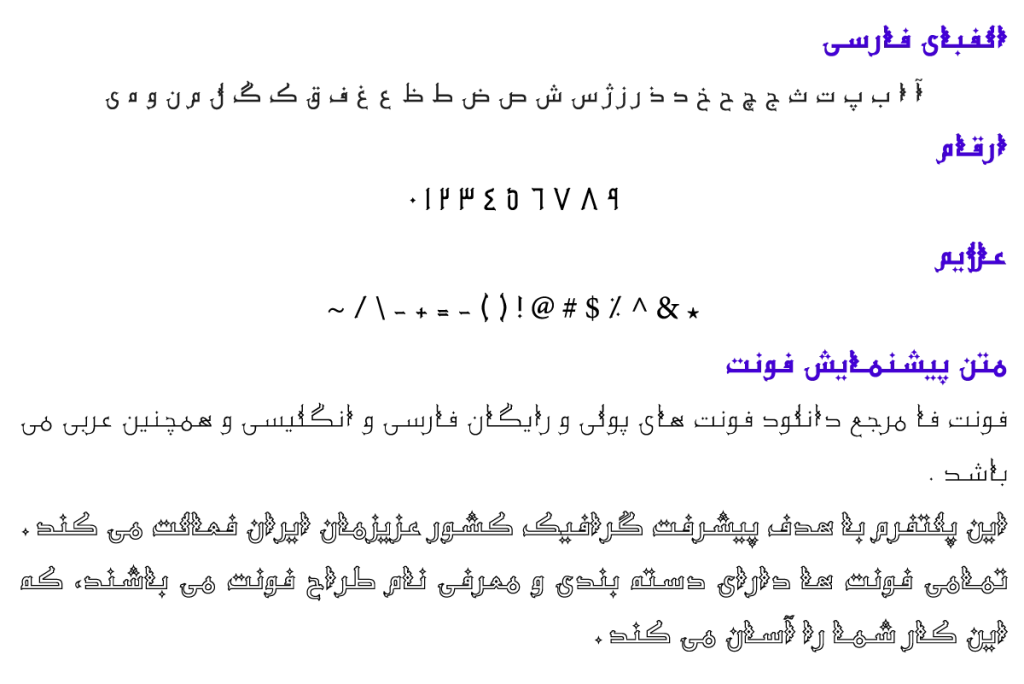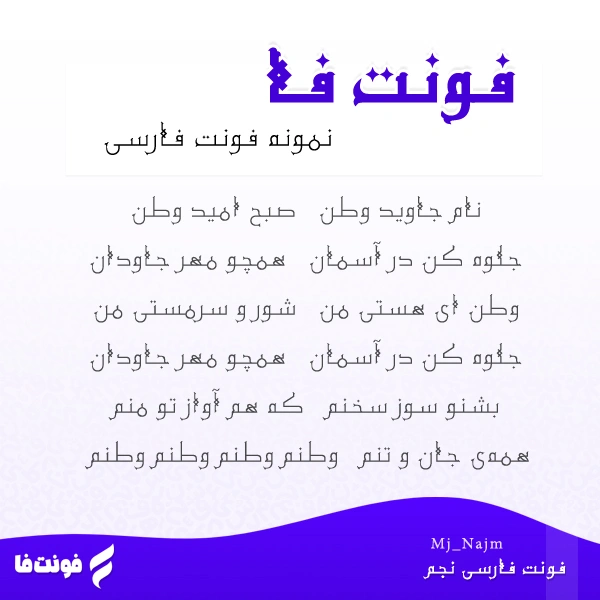
فونت فارسی نجم – Mj Najm
مجموعه فونت: فونت سری Mj
طراح فونت: مجتبی کیا نوع فونت: فونت فانتزی
توضیحات و معرفی فونت نجم
فونت فارسی نجم ( Mj Najm ) از مجموعه فونت های سری Mj می باشد، و نیز نوع فونت فانتزی می باشد.
فونت خوشگل مربوط توسط مجتبی کیا در سال 1390 طراحی و ساخته شده است.
و نیز فونت Mj Najm در 4 وزن پر رنگ و متوسط و معمولی و توخالی خطی است.
- Mj Najm Bold
- Mj Najm Medium
- Mj Najm Regular
- Mj Najm Outline
در تصویر زیر، پیش نمایشی از این تایپ فیس را همراه با شعر زیبای فارسی میبینید.